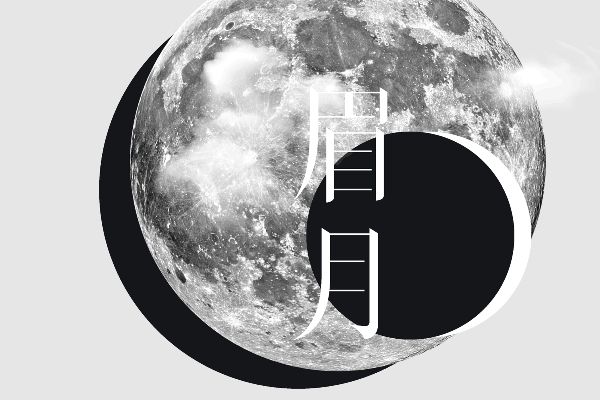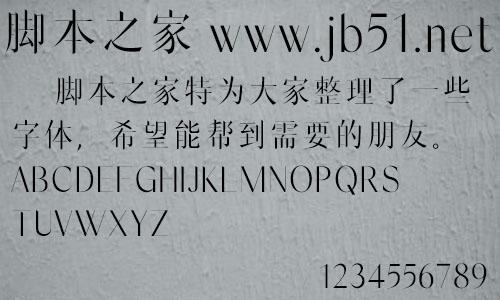
火山字型眉月S01/S02是火山字型推出的火山字型眉月的两种字形,S01字形笔触较S02字形笔触略细,字形端正,适合应用于艺术设计、各类广告和产品包装设计等领域。
火山字型,由一位从业多年的平面设计师创建,每套字体的风格设定皆来自日常设计需求中,从2016年开始成体系的制作中文字库,在2020年6月1日正式公开发行三套原创中文字型——眉月、悍石、修竹。